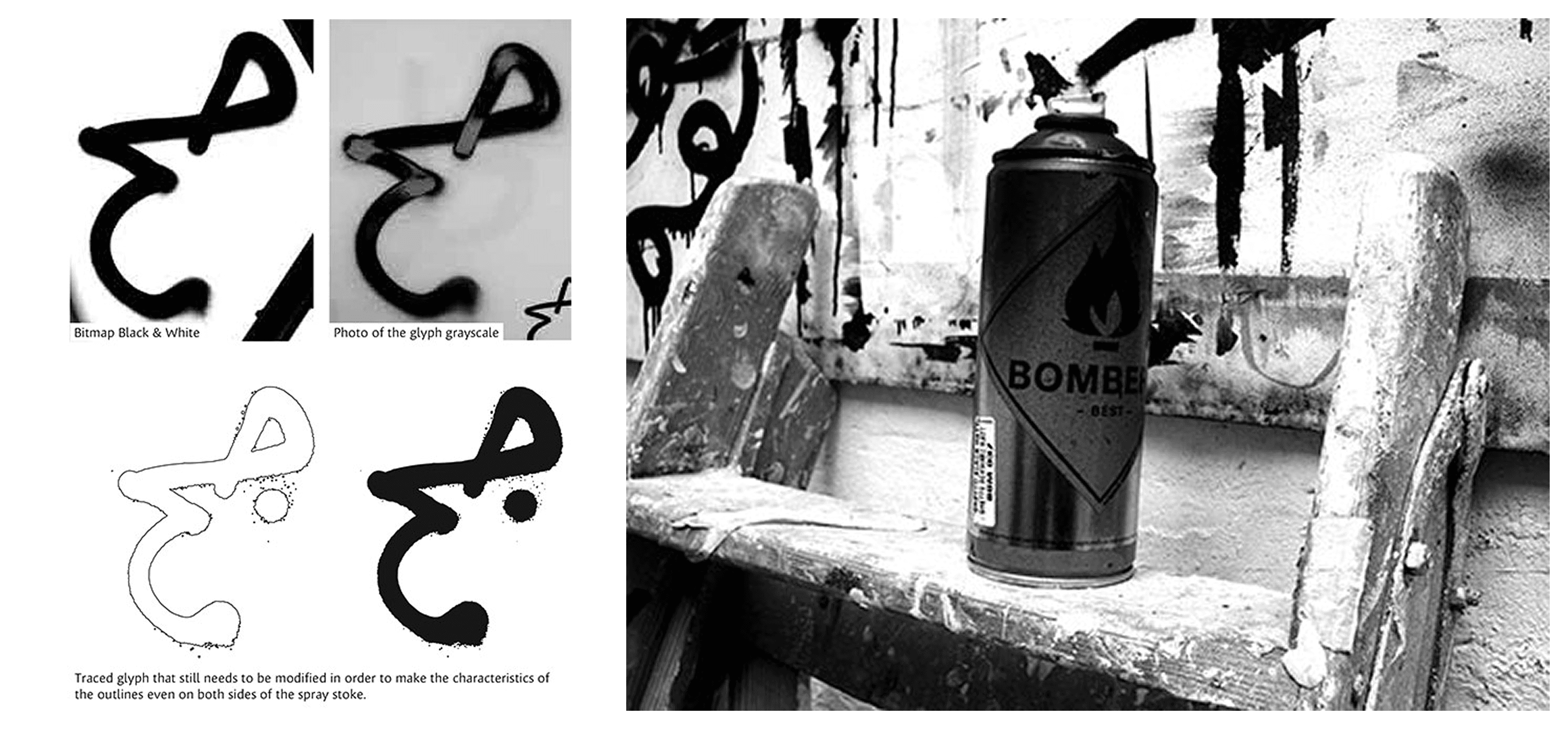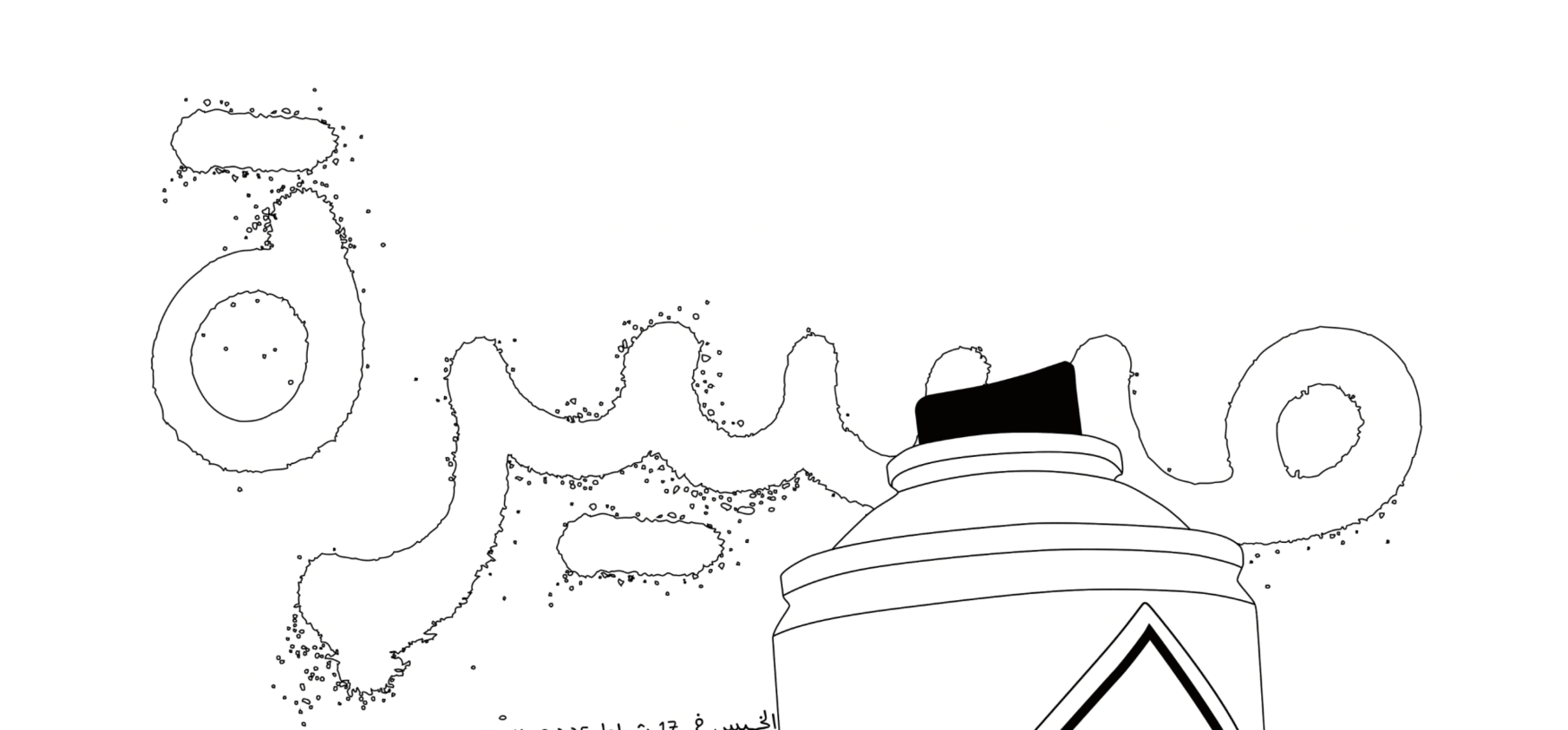
يعكس 29LT Massira روح الحراك الشعبي والاحتجاجات الاجتماعية، بتصميم مستوحى من اللافتات اليدوية التي تُرفع في المظاهرات. يتميز بطابعه العفوي والحر، ما يمنحه قوة تعبيرية وجرأة بصرية لافتة.
الخط مناسب للمشاريع الفنية، الحملات التوعوية، والتصميمات التحرّكية التي تتطلب صوتًا بصريًا جريئًا وغير خاضع للقواعد الكلاسيكية. يدعم العربية والفارسية والأردية.
يعكس 29LT Massira روح الحراك الشعبي والاحتجاجات الاجتماعية، بتصميم مستوحى من اللافتات اليدوية التي تُرفع في المظاهرات. يتميز بطابعه العفوي والحر، ما يمنحه قوة تعبيرية وجرأة بصرية لافتة.
الخط مناسب للمشاريع الفنية، الحملات التوعوية، والتصميمات التحرّكية التي تتطلب صوتًا بصريًا جريئًا وغير خاضع للقواعد الكلاسيكية. يدعم العربية والفارسية والأردية.
يعكس 29LT Massira روح الحراك الشعبي والاحتجاجات الاجتماعية، بتصميم مستوحى من اللافتات اليدوية التي تُرفع في المظاهرات. يتميز بطابعه العفوي والحر، ما يمنحه قوة تعبيرية وجرأة بصرية لافتة.
الخط مناسب للمشاريع الفنية، الحملات التوعوية، والتصميمات التحرّكية التي تتطلب صوتًا بصريًا جريئًا وغير خاضع للقواعد الكلاسيكية. يدعم العربية والفارسية والأردية.